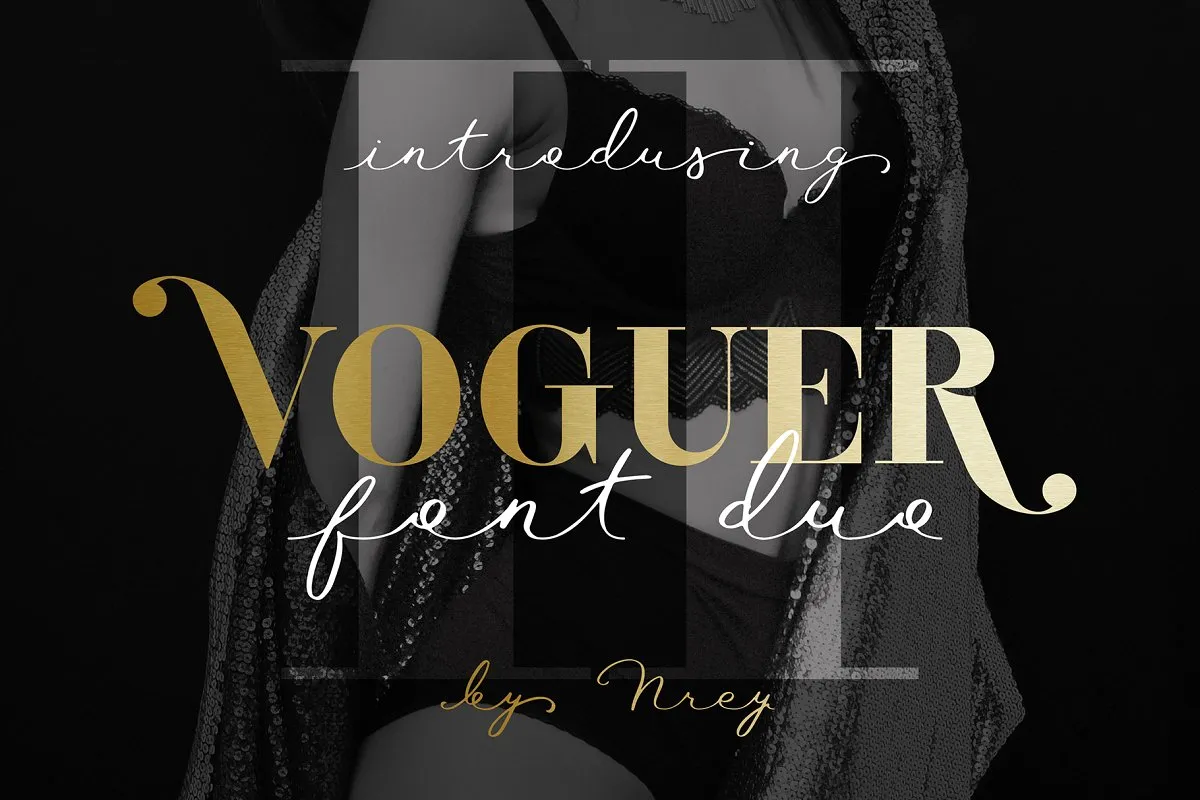
Voguer II Font Duo – Download Grátis
Voguer II Font Duo é uma elegante opção para designers que buscam trazer sofisticação a seus projetos digitais. Esta fonte moderna serifada e script, criada pelo designer Andriy Dykun, oferece um toque de luxo em cada letra com texturas únicas. Inspirado nos estilos gráficos de revistas de moda e na autenticidade das assinaturas escritas a mão, Voguer II II representa perfeitamente o equilíbrio entre modernidade e elegância clássica. Ambas as fontes do Duo contêm suporte multilinguista, alternativas de caracteres e ligaturas belas para adicionar um toque único aos seus designs. É uma escolha ideal para cartões de convite elegantes para casamentos ou para embalar pacotes de beleza e moda com sofisticação. O design cuidadosamente pensado deste Duo oferece opções perfeitas para atender a necessidades diversas, desde o requinte dos cartões de casamento até aos designs de pacote de beleza e estilo fashion.